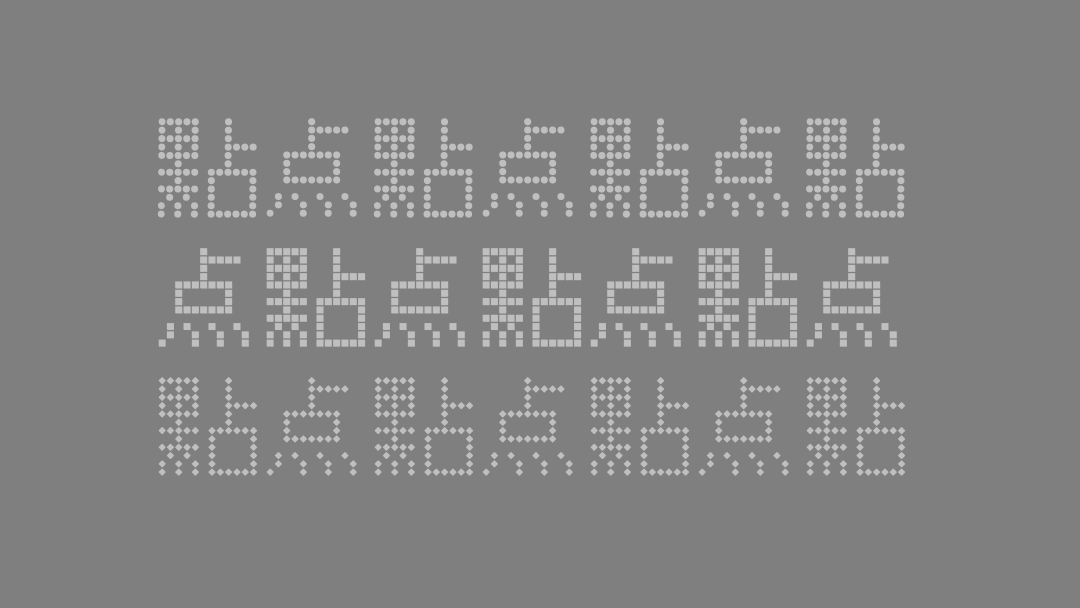
「点点像素」是基于同样以GPL 2.0协议开源的自由字体「文泉驿点阵宋体」,经自动矢量化转换,变形和美化得到的,涵盖超过22000字形的大字符集中文像素艺术字体。「点点像素」使用的将点阵字体自动转换为OpenType字体的源代码也已开源。
目前可见的中文像素艺术字体大多有商业许可协议保护,且很多无法涵盖GBK字符集中的全部汉字字形。「点点像素」及其转换工具提供了从开源点阵字体生成开源像素艺术字体的另一种可能。
前几天我为我们举办的DeeCamp人工智能训练营设计宣传海报的时候,想走复古风,用像素艺术字体来写主要的宣传语。发现网上可找到的一些像素字体,往往都有商业许可协议的保护,或者在制作上只包含GB2312这样的基础字符集。
程序员就喜欢自力更生。就动手写了一个JavaScript转换工具,基于著名的开源字体项目「文泉驿」创建的点阵宋体汉字(目前用的是10pt字型的版本),自动完成所有22000多个字形的矢量化,自动将点阵像素变形为不同修饰风格。
代码写得比较简单。目前发布的v0.1版本的「点点像素」字体只能说初具像素艺术字体的基本模样,大体可用,但后续还有很多优化空间。之后有时间时,会继续优化这个项目,用自动化代码创建更多有趣的字体。